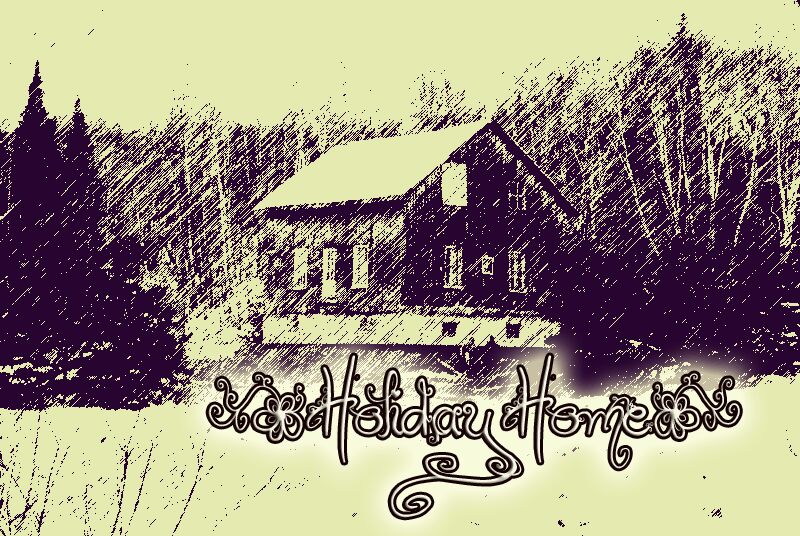
Holiday Home, zaprojektowany przez ETH, to darmowy krój kaligraficzny z wysokimi, płynnymi pociągnięciami i odręcznym stylem. Szerokie pętle spotykają się z drobnymi zawijasami, nadając literom żywą zmianę skali. Drobne detale w kształcie serc i spirali zmieniają pismo w ornament.
Zaproszenia ślubne i branding butikowych kawiarni to zupełnie inne konteksty, ale obfite ozdobniki nadają obu ciepły, osobisty charakter. Krój ten sprawdza się również w projektowaniu opakowań prezentów oraz grafik na wydarzenia sezonowe, zwłaszcza gdy litery mogą mieszać się z wstążkami, liśćmi lub prostymi rysunkami liniowymi. Zaproszenia to jego najbardziej przekonująca rola.